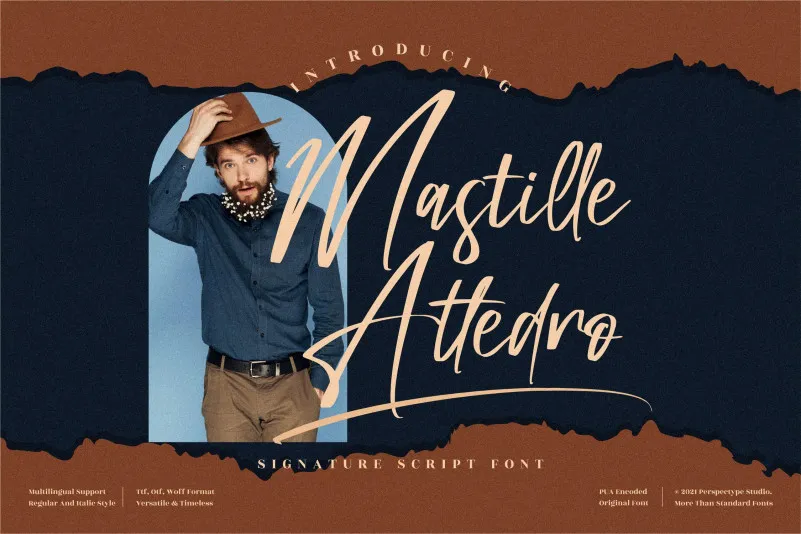
Mastille Attedro Font – Download Grátis
A fonte “Mastille Attedro” é uma elegante fonte cíntica para escrita manuscrita que se destaca por seu aspecto suave e doce, perfeito para aqueles projetos que buscam um toque de alegria e romantismo. Esta fonte é ideal para quem procura uma alternativa charmosa à tipografia tradicional, especialmente em projetos digitais como anúncios online ou design gráfico. Suas linhas leves e seus traços delicados criam um visual agradável e sofisticado, tornando-a perfeita para complementar qualquer projeto, seja ele de comunicação digital ou impressão. A fonte “Mastille Attedro” oferece uma grande flexibilidade que pode ser usada em diversos ambientes, desde textos longos até pequenos detalhes. Ela é perfeita para personalizar materiais promocionais, design gráfico, arte digital e criação de artigos digitais, garantindo um toque romântico a cada projeto com apenas seu simples clique.